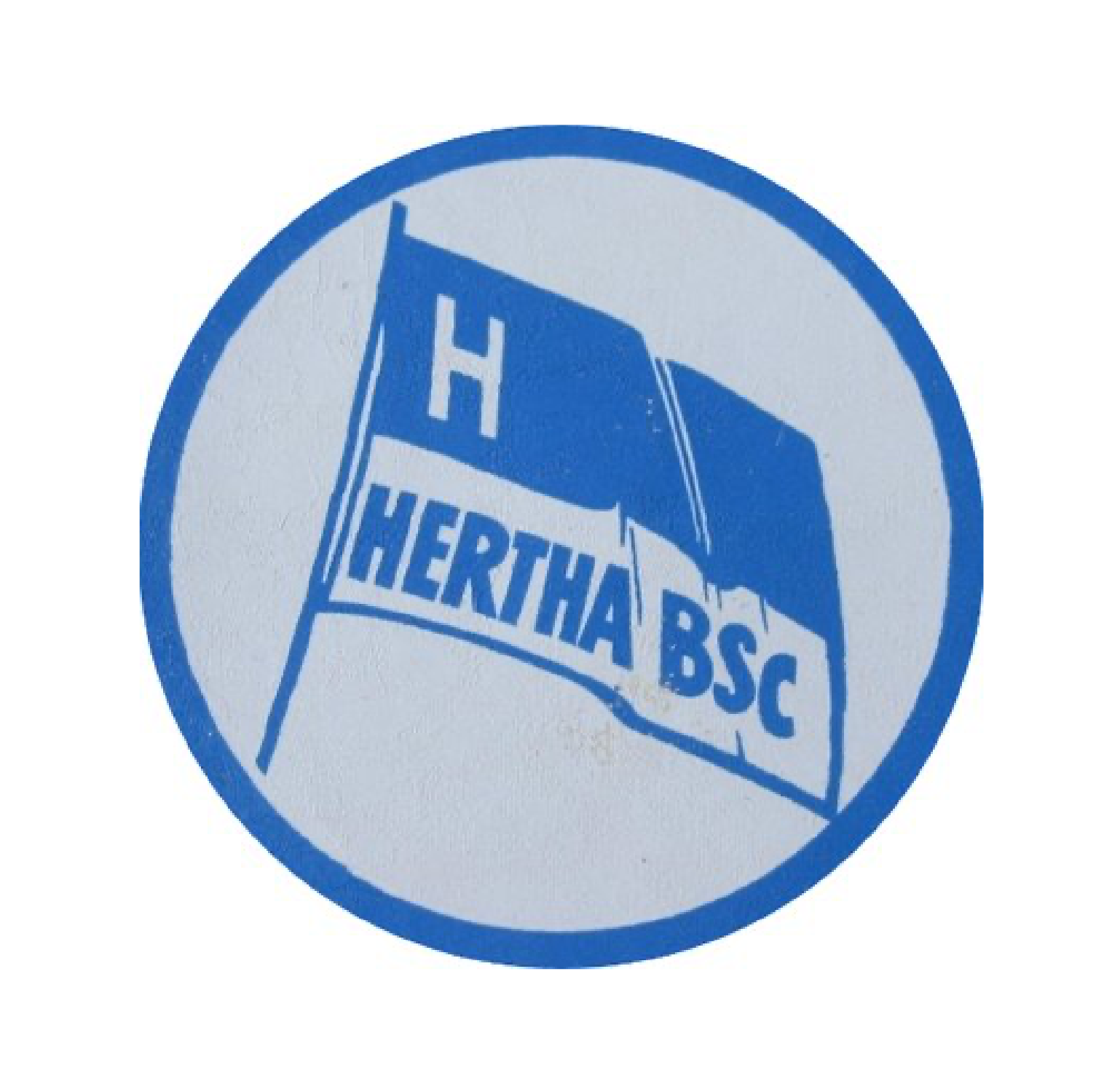
Welche Schrift wurde in diesem Wappen von Hertha BSC aus den 50ern benutzt?
Die Logo-/ Wappengeschichte von Hertha BSC ist praktisch nicht dokumentiert. Die wenigen Informationen, die es gibt, sind widersprüchlich oder falsch. Die Fahne, von der ich die Schrift herausfinden möchte, wurde irgendwann in den 50ern benutzt. Der genaue Zeitraum ist nicht so richtig klar. Das angehangene Bild ist der hochwertigste Scann, den ich finden konnte. Es sieht mir aus, wie ein schmaler Schnitt der Antique Olive. Allerdings scheint das "C" aus der Reihe zu tanzen. Was meinen die Experten?